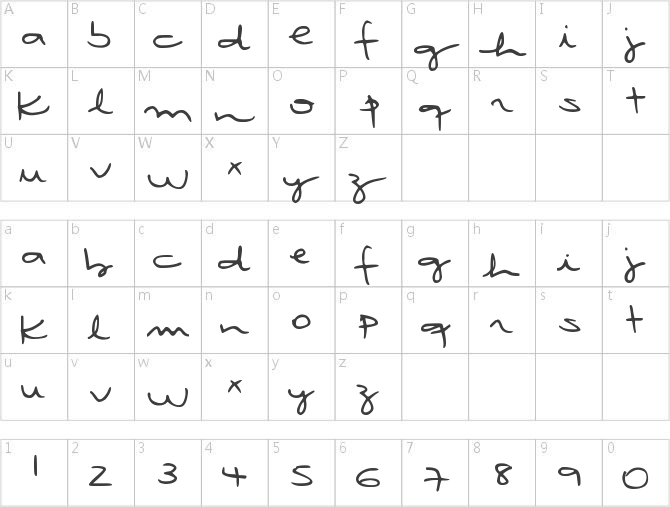
DJB Rubia's Tiny Script
DJB Rubia's Tiny Script介绍
DJB Rubia's Tiny Script字体字库是一款让人赏心悦目、百看不厌的英文字体,适合各类广告和产品包装设计应用,字体大小0.05MB,格式为ttf字体,上传用户是瀨子,作者/版权方为未知